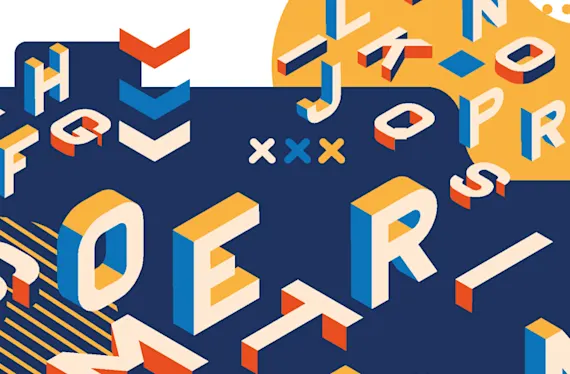
Hoe typografie je klant kan beïnvloeden
Dus je gaat een poster, flyer of folder ontwerpen? Alle emoties die je maar kunt bedenken, geloof het of niet, kunnen worden geuit met behulp van typografie.
Ga jij een poster, flyer of folder ontwerpen? Je hebt dan vast al goed nagedacht over de meeste dingen die je erin wilt verwerken. Zoals wat je wilt zeggen, welke kleuren je gaat gebruiken en waar je je logo gaat plaatsen. Allemaal zeer belangrijke onderdelen van een goede poster en een positief eindresultaat. Maar er is één aspect dat vaak wordt vergeten: typografie.
Wanneer je spreekt, gebruik je zowel je gezichtsuitdrukking als je handgebaren en lichaamshouding om een boodschap over te brengen. Nog los van hetgeen wat je zegt. Maar wanneer je schrijft, zijn daar alleen de woorden voor, toch? Nou, niet helemaal. Als het gaat om geschreven tekst is er een aspect dat in principe dezelfde rol speelt als je lichaamshouding: typografie. Verschillende soorten typografie hebben de kwaliteit om een nieuwe emotie toe te voegen aan tekst.
Er is ondertussen al veel onderzoek gedaan naar dit fenomeen. Als we kijken naar tekst, volgen onze ogen de lijnen van de letters. Dit betekent dat lezen een soort fysieke ervaring is. Je kan het vergelijken met de manier waarop mensen reageren op lichaamstaal. In een onderzoek door Poffenberger en Barrows in 1933, werd er aan mensen gevraagd om emoties toe te kennen aan verschillende vormen. Neerwaartse lijnen gaven de mensen een negatiever gevoel, terwijl opgaande lijnen de respondenten een gevoel van vreugde gaven.
Alle emoties die je je kunt bedenken, geloof het of niet, kunnen worden geuit door middel van typografie. Een aantal psychologen hebben ooit een aantal studenten uit New York een satirisch artikel uit de New York Times laten lezen. Een deel van de groep kreeg het artikel in het font Arial, terwijl het andere deel het artikel kreeg in Times New Roman. Achteraf werd geconcludeerd dat Times New Roman een beter lettertype was voor een satirisch artikel, omdat het grappiger en bozer overkomt.
Al deze informatie kan erg waardevol zijn voor marketeers en grafisch vormgevers. Als je hebt vastgesteld wat het doel is van jouw marketingcampagne of ontwerp weet je precies wat je wilt dat de klant voelt, en kun je de juiste typografie erbij zoeken om dat te bewerkstelligen.